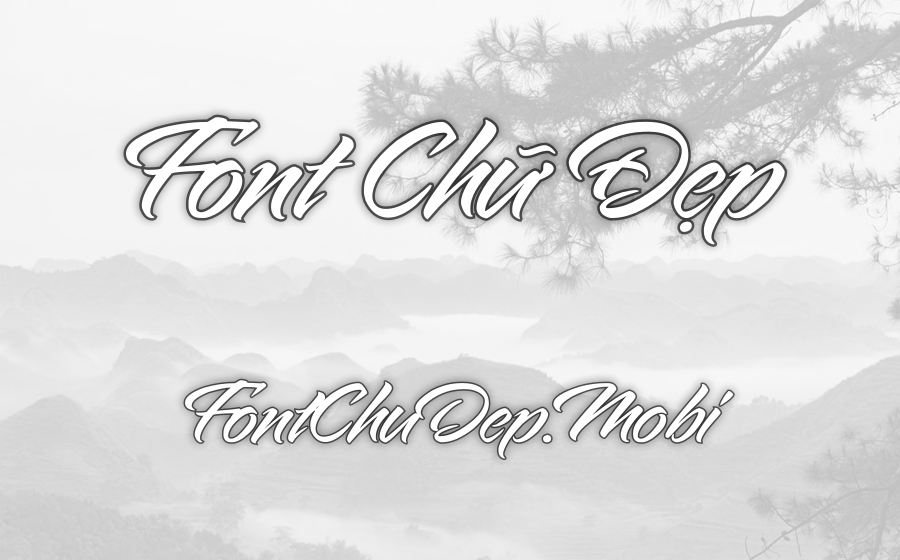
Font UTM Mabella Việt Hóa
UTM Mabella
UTM Mabella là một font chữ nổi bật với phong cách hiện đại và thanh lịch, mang lại cảm giác tinh tế nhờ những đường nét mềm mại được chăm chút tỉ mỉ. Cá nhân tôi khi trải nghiệm font chữ này đã cảm nhận được sự sang trọng và chuyên nghiệp mà nó mang lại cho các thiết kế thương hiệu và đồ họa. Với việc hỗ trợ đầy đủ tiếng Việt cùng hơn 200 ngôn ngữ khác, font này do Thiên Minh Việt hóa thực sự là một lựa chọn đa năng và phù hợp với nhiều dự án sáng tạo. Điều này chắc chắn sẽ làm hài lòng người dùng, khi mà FontChuDep.mobi đã khéo léo sưu tầm và giới thiệu font UTM Mabella để đáp ứng nhu cầu ngày càng cao của bạn đọc, cùng với việc cung cấp nguồn tham khảo chất lượng cao và hữu ích.
Khi điểm qua các đặc điểm thiết kế, UTM Mabella gây ấn tượng mạnh với những nét chữ mềm mại, độ tương phản vừa phải và phong cách độc đáo. Font chữ này rất lý tưởng cho các ứng dụng như thiết kế logo, thiệp mời, biển hiệu, tiêu đề trang web và nhiều ấn phẩm sáng tạo khác. Những ngành nghề như quảng cáo, ẩm thực, thiệp cưới, và giáo dục sẽ thấy UTM Mabella là một công cụ đắc lực giúp tạo điểm nhấn đầy tinh tế, đem lại sự thanh lịch cho mọi sản phẩm thiết kế của họ. Trải nghiệm font chữ này thực sự là một điều thú vị đối với bất cứ ai yêu thích sự mới mẻ và sự thanh thoát trong các tác phẩm đồ họa.